Bạn có biết font chữ Calligraphy được rất nhiều designer chuyên nghiệp sử dụng trong các dự án thiết kế không? Với vẻ đẹp mềm mại và tinh tế, font Calligraphy lập tức thu hút người xem ngay từ ánh nhìn đầu tiên. Để tải font chữ Calligraphy Việt hóa, bạn hãy tham khảo trong bài viết dưới đây.
Tìm hiểu về font chữ Calligraphy
Font chữ Calligraphy Việt hóa là gì?
Font chữ Calligraphy (hay còn được gọi là Beautiful Writing) là một loại font đặc biệt lấy cảm hứng từ chữ viết tay hoa mỹ. Điểm đặc biệt nhất của font chữ này chính là đường nét uốn lượn mềm mại, điêu luyện và tỉ mỉ. Với vẻ đẹp sắc sảo, Calligraphy mang đến sự tinh tế và làm nổi bật nét cá nhân cho những sản phẩm thiết kế sử dụng font chữ này.
Font chữ Calligraphy được Việt hóa mang đến sự tinh tế và sang trọng cho các bản thiết kế. Các chữ cái trong font này thường có sự biến đổi giữa đậm và nhạt, tạo nên sự cân đối và thu hút chú ý đến từng chi tiết. Điều này giúp làm nổi bật thông điệp và tạo sự khác biệt cho thiết kế.
Không chỉ dừng lại ở vẻ đẹp thẩm mỹ, font chữ Calligraphy còn truyền tải một phần về nghệ thuật và tâm hồn của người viết. Calligraphy tạo ra cảm giác cá nhân và sâu lắng, đặc biệt phù hợp cho các dự án quan trọng như thiệp cưới, thư mời hay bất kỳ thiết kế nào muốn tạo dấu ấn riêng.
Sử dụng font chữ Calligraphy trong trường hợp nào?
Với những đường nét uốn cong nổi bật và thu hút, font Calligraphy thường được designer chuyên nghiệp ưu tiên sử dụng trong các thiết kế quan trọng như:
- Thiệp cưới
- Thư mời
- Biểu ngữ, đồ họa sự kiện
- Logo thương hiệu
- Bìa sách
- Các tài liệu đòi hỏi tính thẩm mỹ và cá nhân hóa cao
Với vô vàn các ứng dụng khác nhau, Calligraphy hứa hẹn sẽ là font chữ thẩm mỹ, tinh tế giúp nâng tầm thiết kế của bạn đấy!
Các mẫu font chữ Calligraphy Việt hóa nổi bật
Bellissima Script Pro
Bellissima Script Pro là font chữ hoàn hảo cho những người yêu thích nghệ thuật viết chữ đẹp. Font chữ này được thiết kế bởi Alejandro Paul với nguồn cảm hứng xuất phát từ quyển sách dạy viết chữ đẹp "Bellezas de la Caligrafía" của Ramón Stirling xuất bản năm 1844.
Bellissima Script Pro có hơn 2000 ký tự mở rộng và được tác giả thiết kế tối giản để phù hợp với nét chữ hiện đại nhưng vẫn giữ được những đường nét tinh tế của những năm 1800. Đây được xem là sự kết hợp tuyệt vời giữa thiết kế hiện đại và nghệ thuật viết tay truyền thống.
Araulga Laudery Regular
Araulga Laudery Regular là bộ font chữ độc đáo được sáng tạo bởi Insan Nurbahagia với nhiều ký tự thay thế uốn lượn. Đường nét của font chữ này được cho là phù hợp với các thiết kế thiệp cưới, trang trí và tiêu đề. Sử dụng font Araulga Laudery Regular giúp mang lại sự tươi mới và tôn lên nét độc đáo cho bản thiết kế.
Parfumerie Script 2 và Parfumerie Script Curly
Được sáng tạo đặc biệt dành cho các dự án thiết kế liên quan đến đám cưới và thiệp mời, font Parfumerie Script 2 và Parfumerie Script Curly đều có đường nét chính uốn cong mềm mại, kèm theo đó là những đường nét râu ria không kém phần hoa mỹ. Cả hai kiểu font này đều đem đến vẻ đẹp trang nhã và tinh tế cho thiết kế, đồng thời giúp gợi lên cảm giác sang trọng khi nhìn vào tác phẩm.
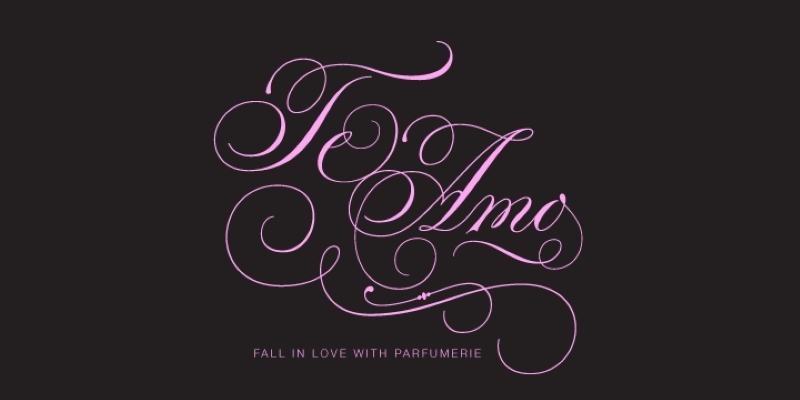
Font Bilgate
Bilgate là font chữ mang hơi hướng cổ điển với những đường nét đầy đặn và độc đáo. Font chữ này là lựa chọn tuyệt vời cho các bản thiết kế logo, bao bì và trang trí thiệp mời. Điểm đặc trưng của font chữ này là sự pha trộn giữa vẻ đẹp hiện đại và cổ điển, giúp tạo nên những thiết kế độc đáo thu hút ánh nhìn.